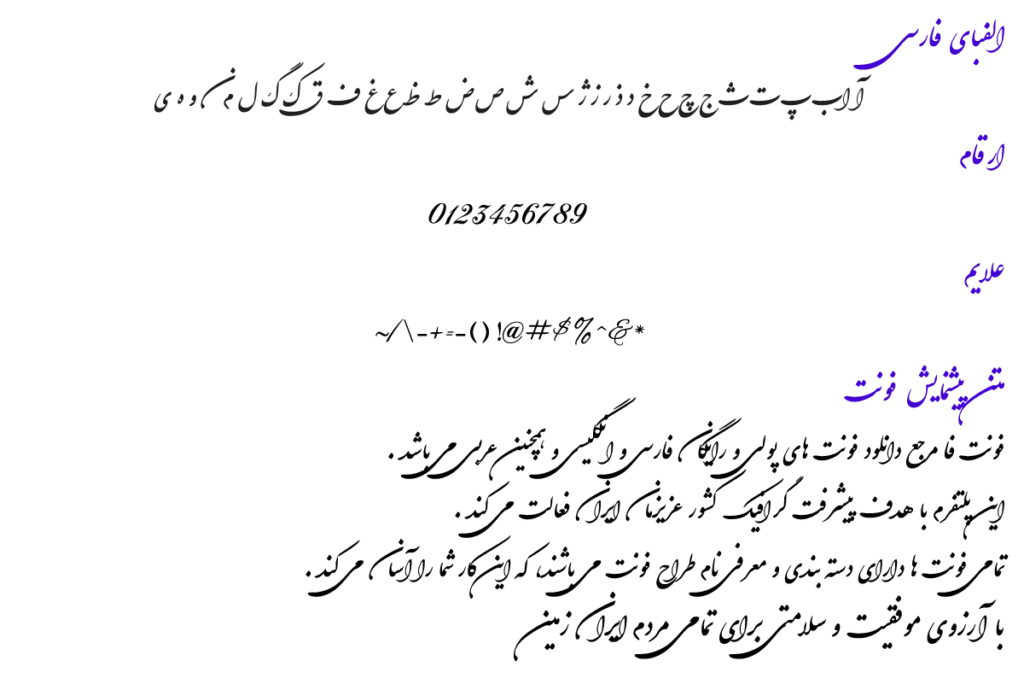
فونت فارسی نستعلیق شکسته – Shekasteh
سال ساخت فونت: 1396
نوع فونت: فونت خوشنویسی
توضیحات و معرفی فونت نستعلیق شکسته
فونت فارسی نستعلیق شکسته ( Shekasteh ) از مجموعه فونت های آزاد می باشد، همچنین نوع فونت خوشنویسی می باشد.
فونت فوق العاده زیبای معرفی شده در سال 1396 طراحی و ساخته شده است.
نستعلیق شکسته فونتی خوشگل است که تفاوتی زیادی با فونت نستعلیق دیما شکسته دارد.
همچنین فونت نستعلیق شکسته در یک وزن معمولی است.